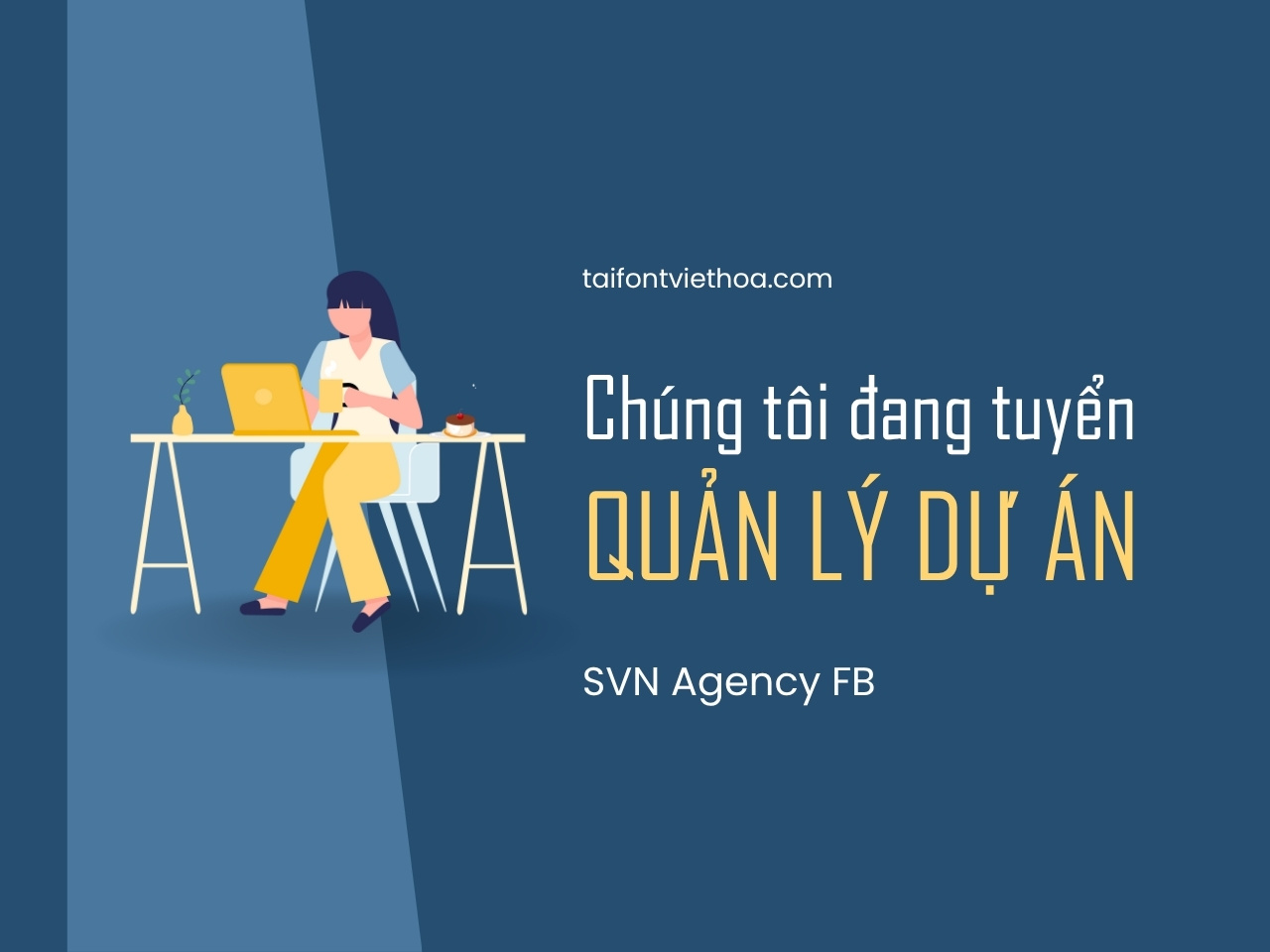
Font việt hóa SVN Agency Fb đầy đủ
Giới thiệu về font SVN Agency Fb Trọn Bộ – Kiểu chữ sans-serif hiện đại, mạnh mẽ và chuyên nghiệp
SVN Agency Fb Trọn Bộ là phiên bản Việt hóa của font Agency Fb – một kiểu chữ sans-serif mang phong cách hiện đại, mạnh mẽ và rất chuyên nghiệp. Font được thiết kế với các nét chữ sắc nét, dày dặn và cân đối, phù hợp cho các dự án thiết kế thương hiệu, quảng cáo và truyền thông kỹ thuật số.
Phiên bản Việt hóa của SVN Agency Fb Trọn Bộ hỗ trợ đầy đủ dấu tiếng Việt cùng hơn 70 ngôn ngữ khác. Font giúp các nhà thiết kế dễ dàng áp dụng trong nhiều dự án đa dạng mà vẫn giữ được phong cách trẻ trung, chuyên nghiệp và nổi bật.
Thiết kế sans-serif đậm nét – Ứng dụng đa dạng trong thương hiệu và quảng cáo
SVN Agency Fb Trọn Bộ sở hữu các nét chữ đậm, rõ ràng và cân đối, tạo cảm giác mạnh mẽ và thu hút. Font phù hợp sử dụng cho tiêu đề, banner, logo hoặc poster cần sự ấn tượng và nổi bật. Phong cách thiết kế của Agency Fb rất thích hợp với các dự án công nghệ, thể thao, quảng cáo và thương hiệu hiện đại, năng động.
Ứng dụng lý tưởng: thiết kế logo, poster quảng cáo, banner sự kiện, nhận diện thương hiệu thể thao, website công nghệ và các dự án marketing sáng tạo. Ngành nghề phù hợp: công nghệ, thể thao, giải trí, quảng cáo, thương mại điện tử và startup sáng tạo.
Thiết kế: Rod McDonald, Nadine Cahine